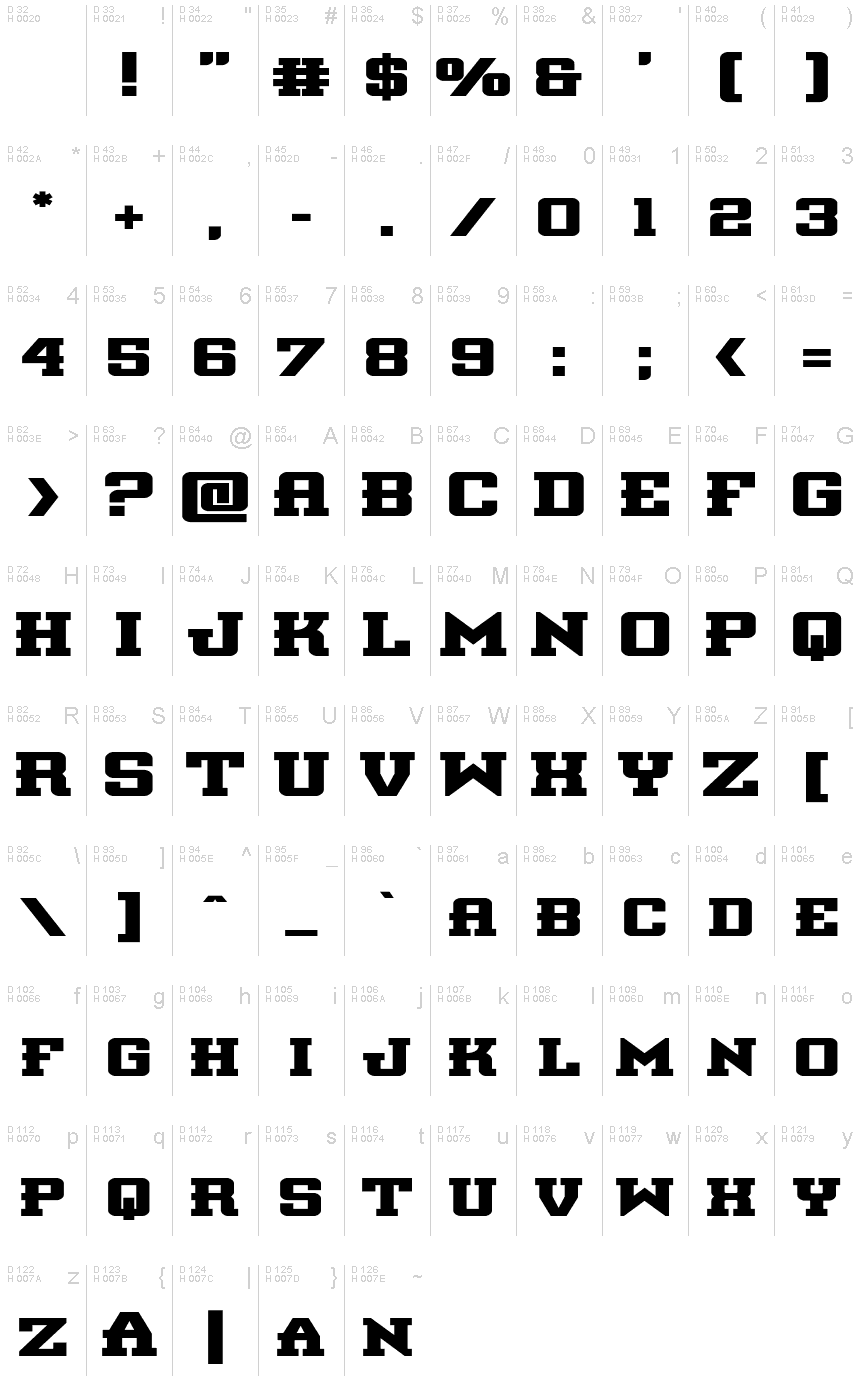
Interceptor Bold Expanded od Iconian Fonts to darmowy krój pisma typu display w stylu retro, który wyróżnia się masywnym charakterem, przywodzącym na myśl szyldy automatów do gier i logotypy science-fiction z końca lat 70. Litery są szerokie, blokowe i o ostrym kroju, z kwadratowymi narożnikami, głębokimi wcięciami i silnym, poziomym naciskiem, co nadaje każdemu słowu mechaniczny, „stemplowany” wygląd.
Dzięki temu ten darmowy font świetnie sprawdza się w tytułach plakatów, brandingu gier, na okładkach komiksów, w planszach tytułowych do streamingu oraz wyrazistych opakowaniach, gdzie liczy się klimat retro-tech. Użyj go wszędzie tam, gdzie krótkie nagłówki, logotypy lub monogramy mają sprawiać wrażenie potężnych i technicznych – wielkie litery niosą ze sobą wbudowany ładunek siły i nie wymagają dodatkowych zdobień.
Interceptor Bold Expanded